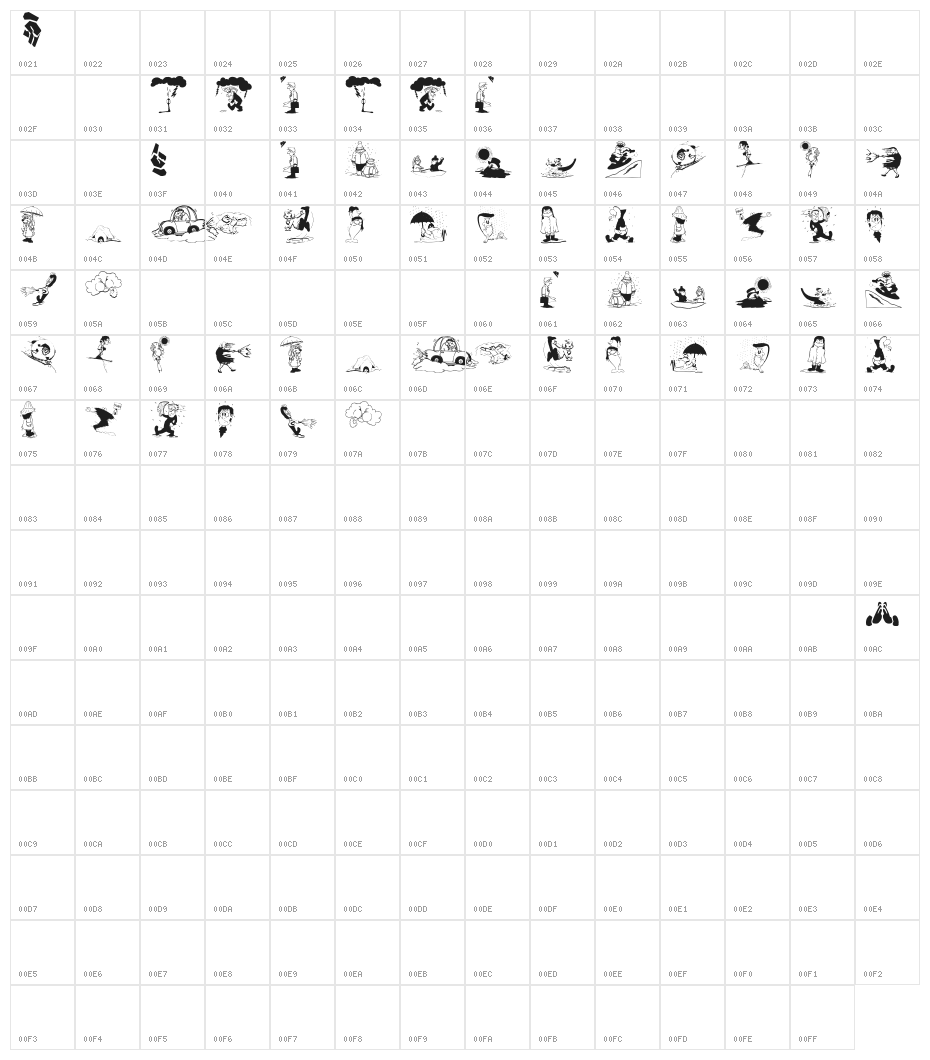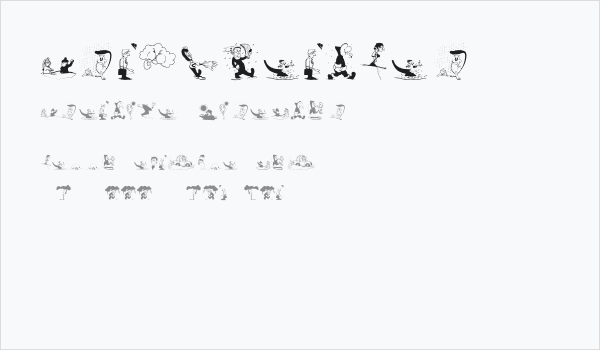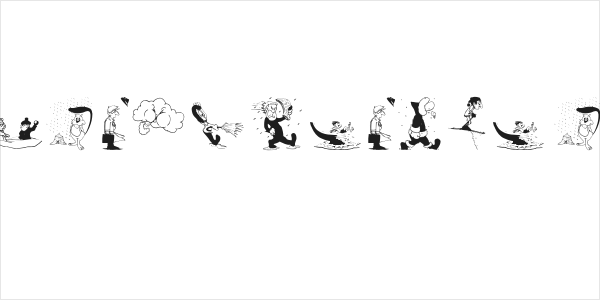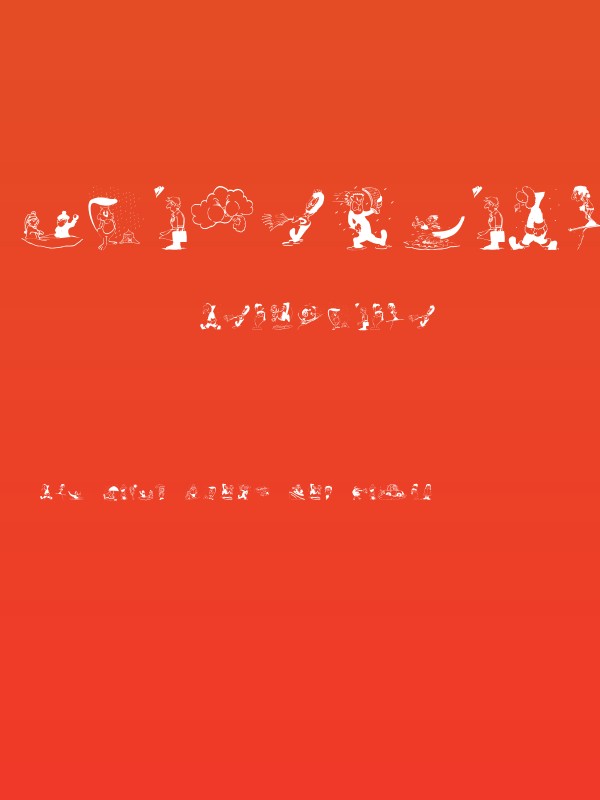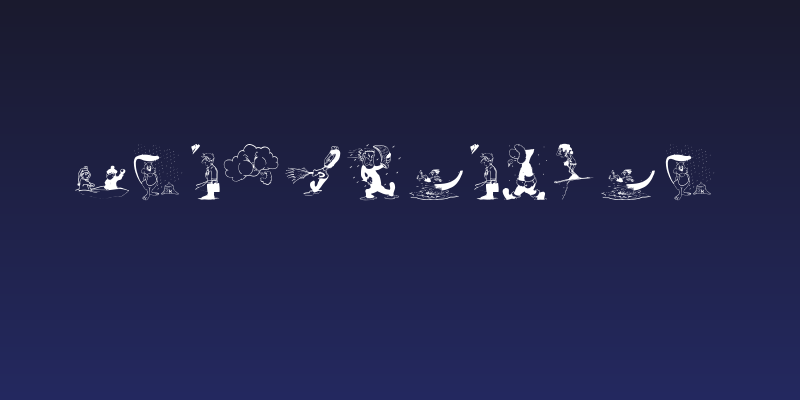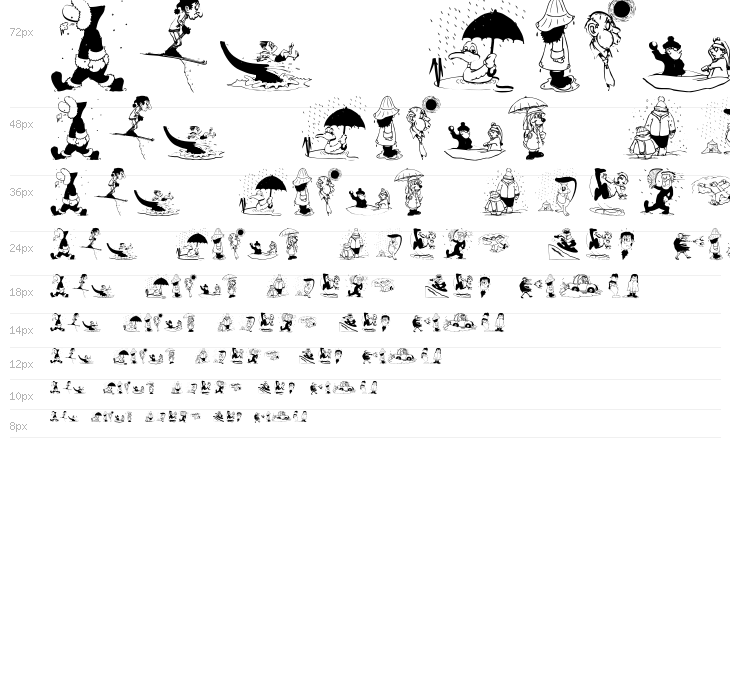
CrazyWeather Font
| Stile generale | Playful, Whimsical, Decorative |
| Caso d'uso | Illustrative icons, Thematic graphics, Decorative accents |
| Progetti proposti | Children's books, educational materials, weather apps, playful posters, greeting cards. |